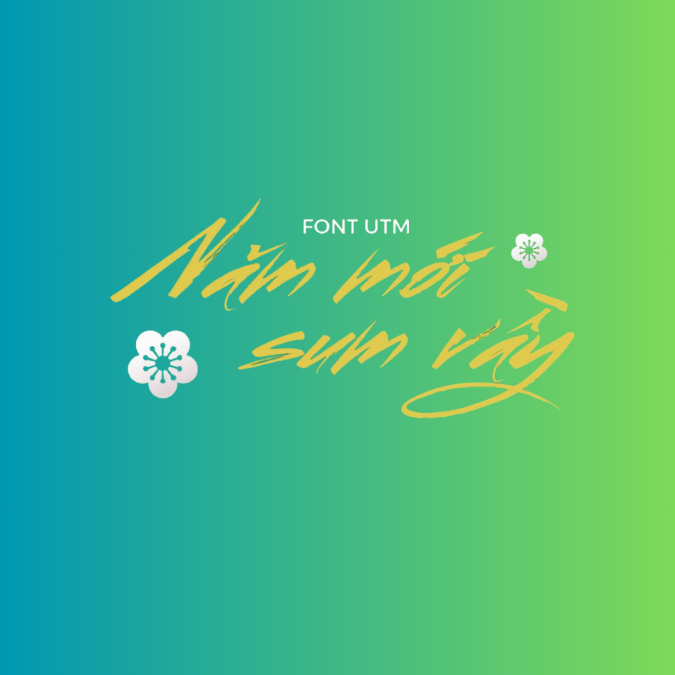
Việt hóa font UTM Ông Đồ Trẻ ,font Tết
Việt hóa font UTM Ông Đồ Trẻ và font Tết
1. Font UTM Ông Đồ Trẻ:
- UTM Ông Đồ Trẻ là một font chữ mang đậm phong cách truyền thống Việt Nam, thường được sử dụng trong các tác phẩm nghệ thuật, thiệp cưới, và trang trí Tết.
- Font chữ này có thiết kế mềm mại, uốn lượn, thể hiện nét đẹp văn hóa dân gian và sự nhẹ nhàng trong từng chữ cái.
- Việt hóa font này giúp người dùng dễ dàng viết và thể hiện những lời chúc tốt đẹp trong các dịp lễ hội, đặc biệt là Tết Nguyên Đán.
2. Font Tết:
- Font Tết thường được thiết kế với những họa tiết, hình ảnh đặc trưng của ngày Tết như hoa mai, hoa đào, câu đối.
- Đặc điểm của font này là sự phong phú về kiểu dáng và màu sắc, mang lại cảm giác vui tươi, ấm áp cho không khí ngày Tết.
- Việt hóa font Tết giúp tạo ra các mẫu thiệp chúc mừng, banner trang trí và các sản phẩm liên quan đến lễ hội, làm cho trải nghiệm ngày Tết thêm phần ý nghĩa.
Ứng dụng
- Cả hai font chữ này đều rất thích hợp cho việc thiết kế đồ họa, quảng cáo, và các sản phẩm truyền thông trong dịp lễ hội, giúp giữ gìn và phát huy bản sắc văn hóa Việt Nam.